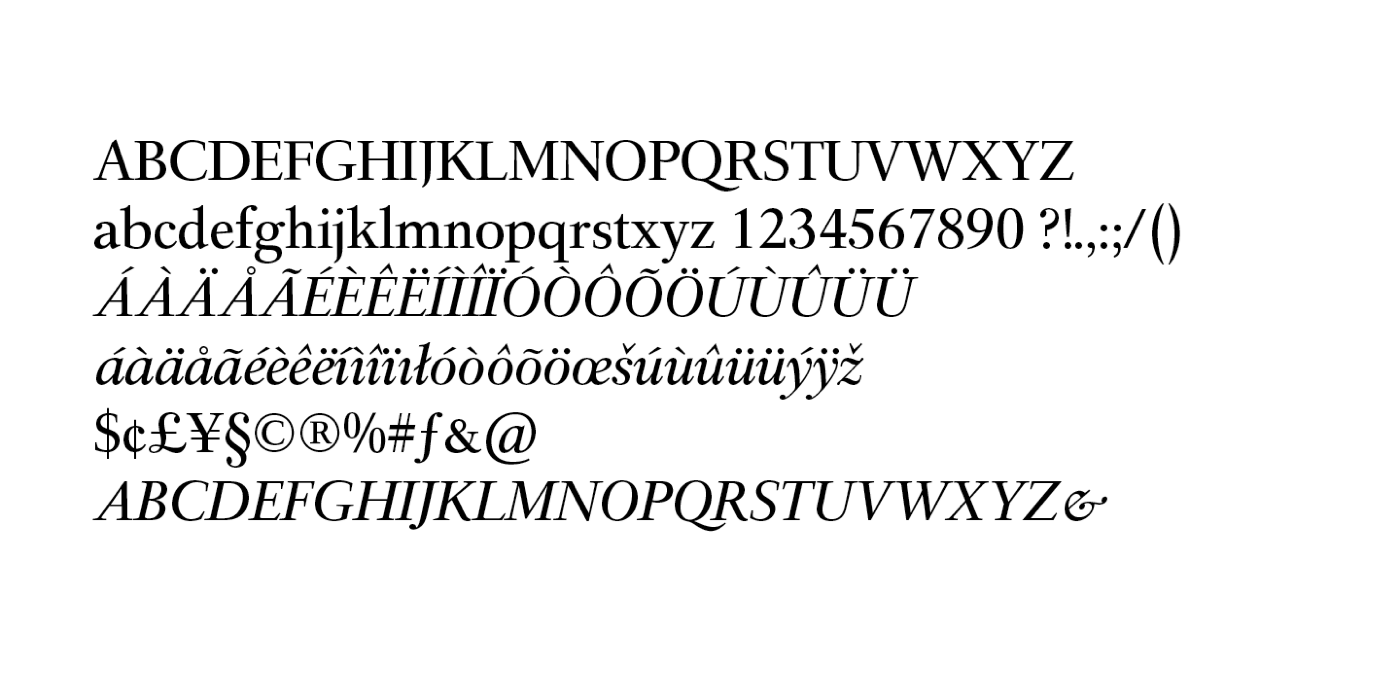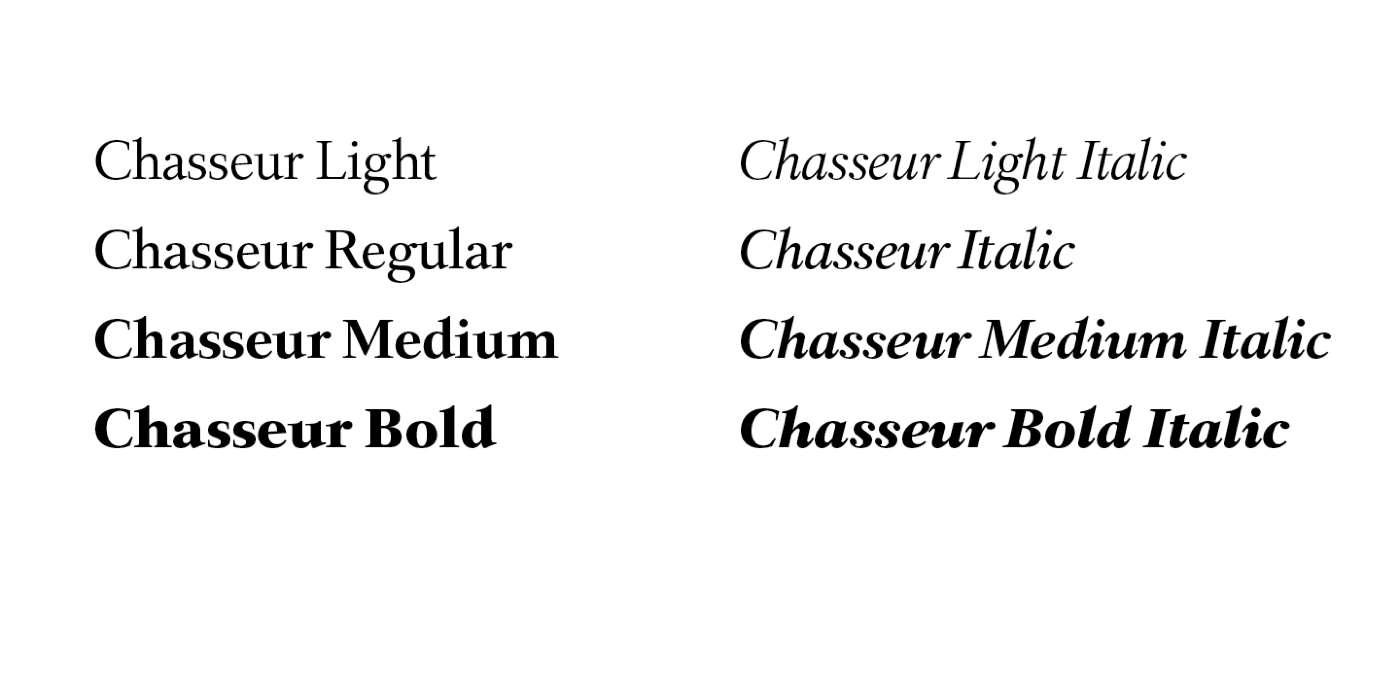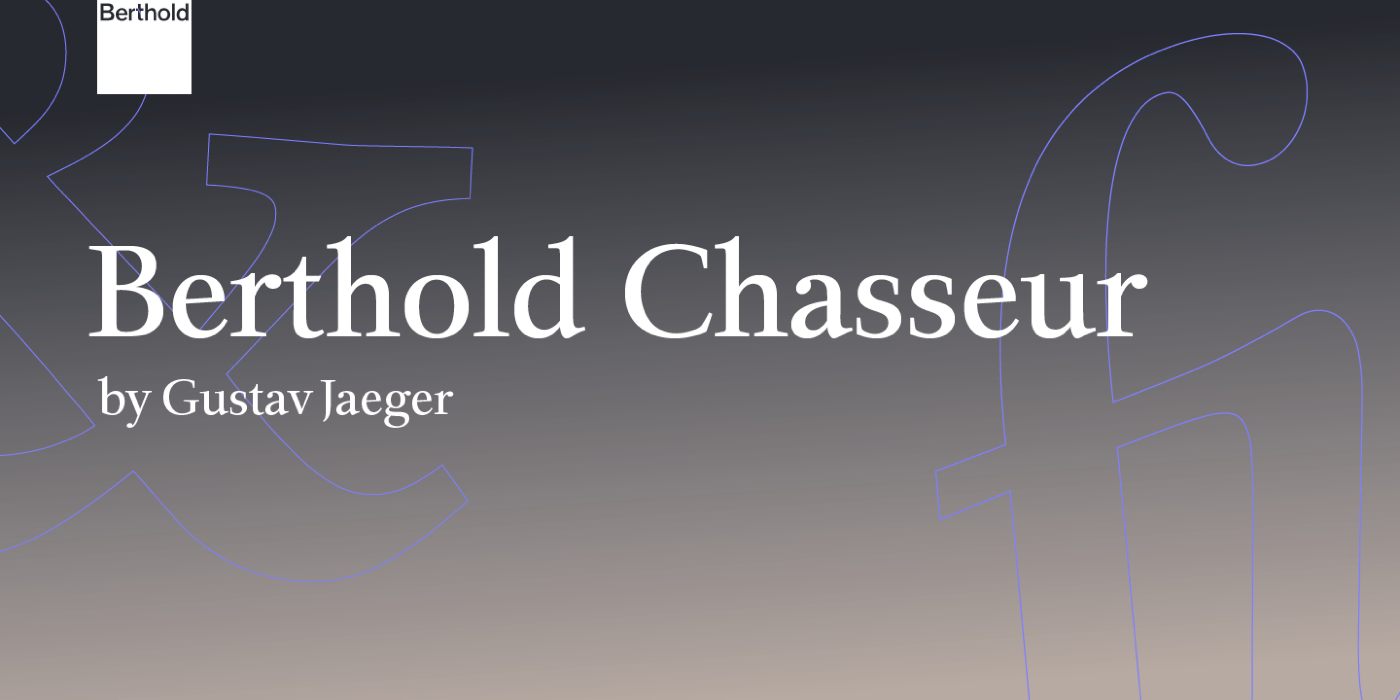
Die Chasseur ist eine Antiqua-Familie von Gustav Jaeger und erschien Ende der 1980er-Jahre bei der H. Berthold AG. Die Schrift besteht aus vier Strichstärken mit Kursiven. Die Schnitte sind heute mit westeuropäischer Belegung über Monotype verfügbar.